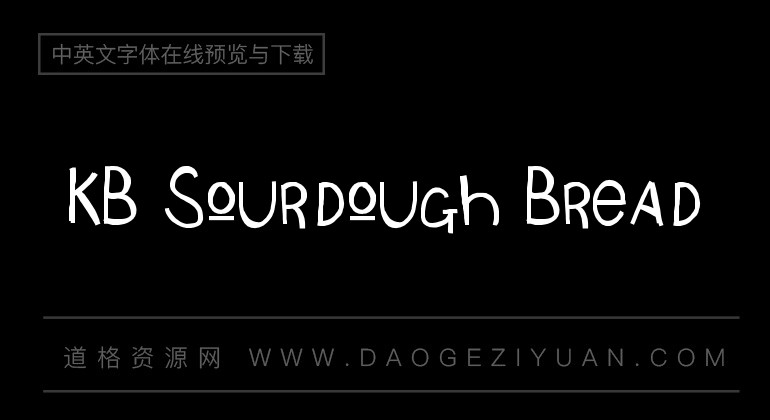
KB Sourdough Bread是一款手写字体,由Konstantin Bolotov设计,他是一位俄罗斯设计师。字体灵感来自传统的酵母面包,它具有温暖和自然的外观,可以用于品牌标识,卡片,海报,海报和其他设计项目。KB Sourdough Bread字体包含有大量的变体,可以满足您的不同需求。它的设计风格既有传统感又有现代感,可以为您的项目带来活力和温暖。内容介绍
KB Sourdough Bread是一款非常不错的手写艺术字体,具有很好的视觉感,适合于文化类的宣传设计、商业类品牌的广告和产品包装设计以及个性化文字排版等较多场景。